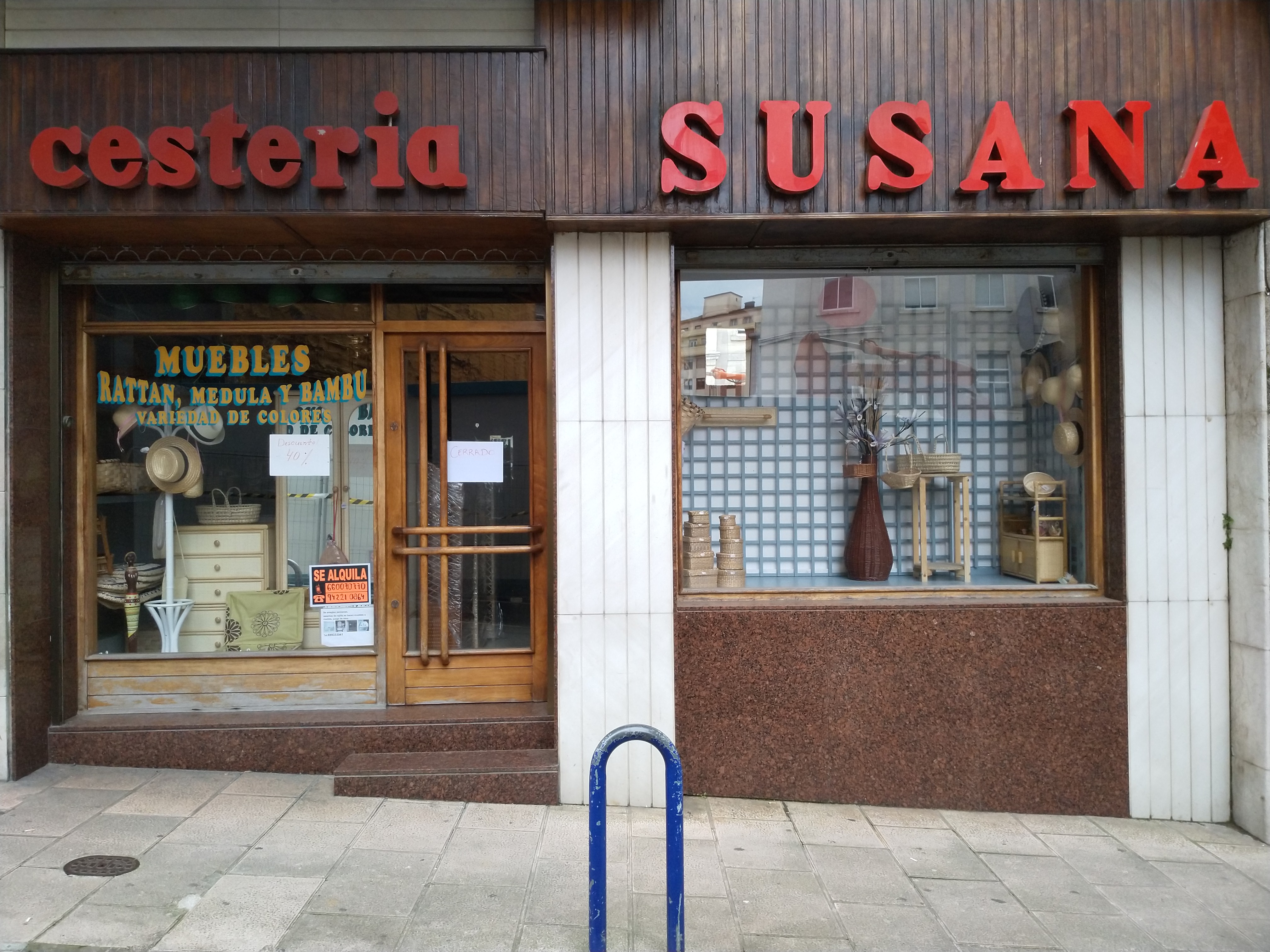
Cestería Susana
Después de 90 años, en abril de 2019 cerró sus puertas una de las últimas cesterías de Cantabria (y última de Santander). Desde entonces, era habitual pasar por la calle Francisco de Quevedo y seguir viendo su fachada y su rótulo con grandes letras corpóreas, y ese vidrio rotulado.
Hace poco comenzaron unas obras en el local y todo esa fachada ha desaparecido. Con ella el rótulo. Y con ello una parte de la historia comercial de Santander. Desconocemos su destino, y estamos tratando de averiguarlo, pero o se ha convertido en chatarra (como ocurrió con La Mejillonera) o lo veremos que se vende en páginas de objetos de segunda mano.
Desde Santatipo y la Red Ibérica en Defensa del Patrimonio Gráfico, estamos luchando para que esto no ocurra. Queremos que los rótulos sean parte de nuestras ciudades, porque nos cuentan historias locales y nos han dotado de identidad. Nos hablan de otra sociedad, otros negocios que no existen, otras costumbres.
Queremos que se queden en su sitio. Pero no siempre es posible y por ello les recogemos y les preservamos, para su protección y puesta en valor como #PatrimonioGráfico de las ciudades.
No podemos dejar que desaparezcan sin más, porque con ellos desaparece parte nuestra memoria colectiva.
Salvemos los rótulos y gráfica comercial.